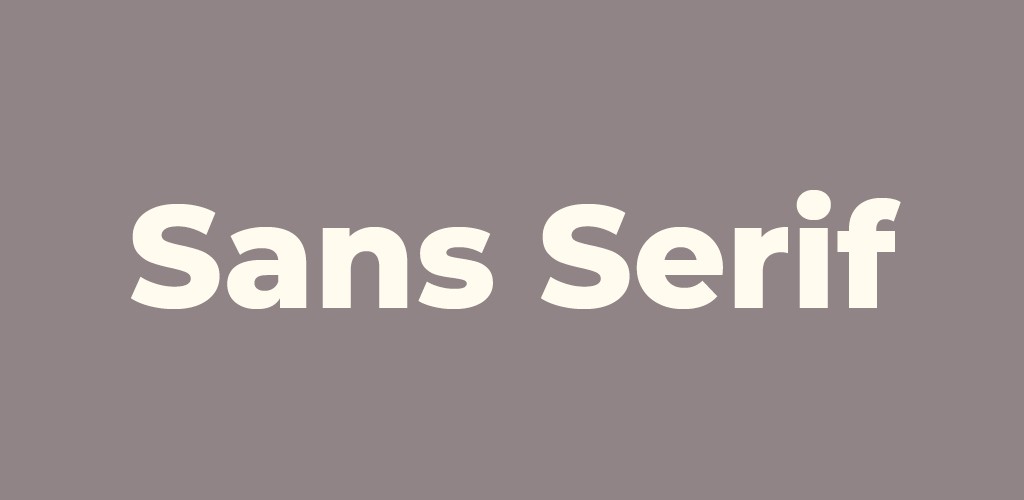
Font chữ là một thành tố quan trọng trong quá trình thiết kế ấn phẩm hoàn chỉnh. Trong bài viết này, hãy cùng ColorME tìm hiểu về font Sans Serif rất quen thuộc với các designer nhé !
Theo nghĩa Latin, sans serif nghĩa là “without serif – không có chân”, tức là kiểu font chữ không có chân. Đặc điểm “nhận dạng” dễ thấy nhất của font chữ này là gọn gàng, hiện đại, nét chữ gần như đều nhau.